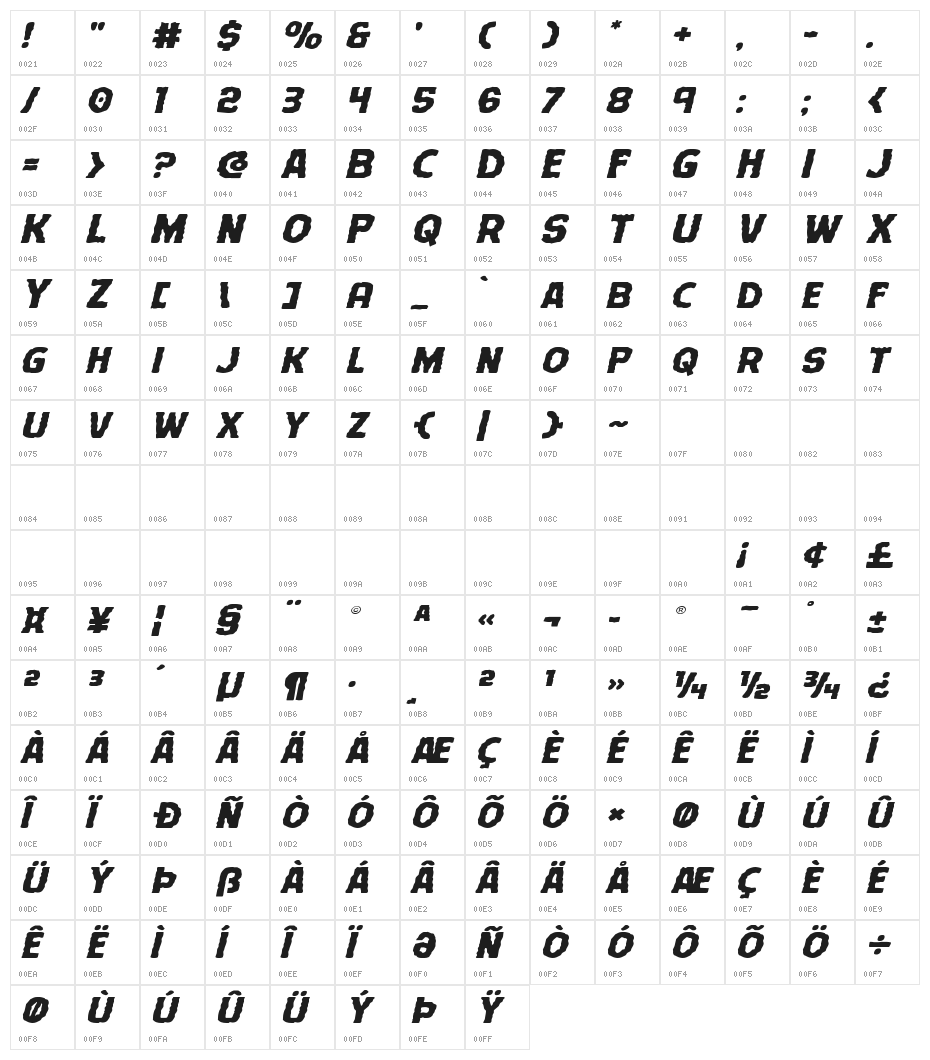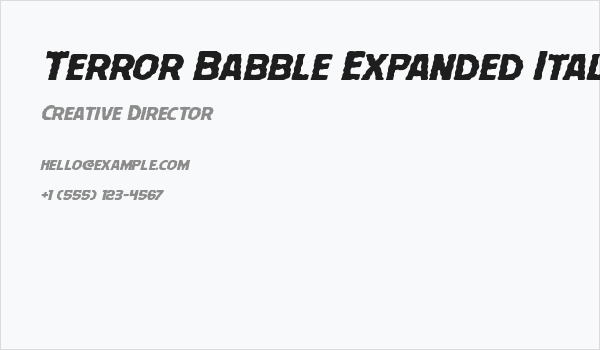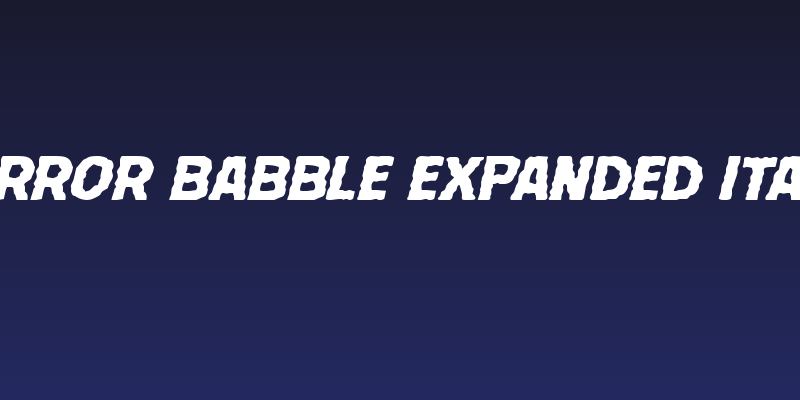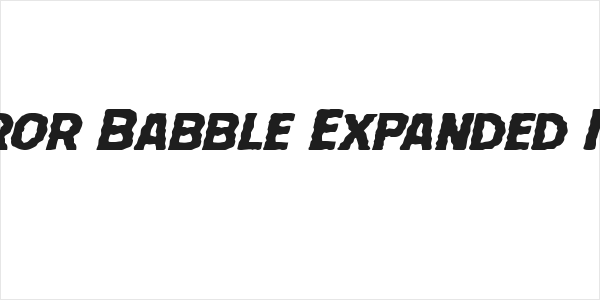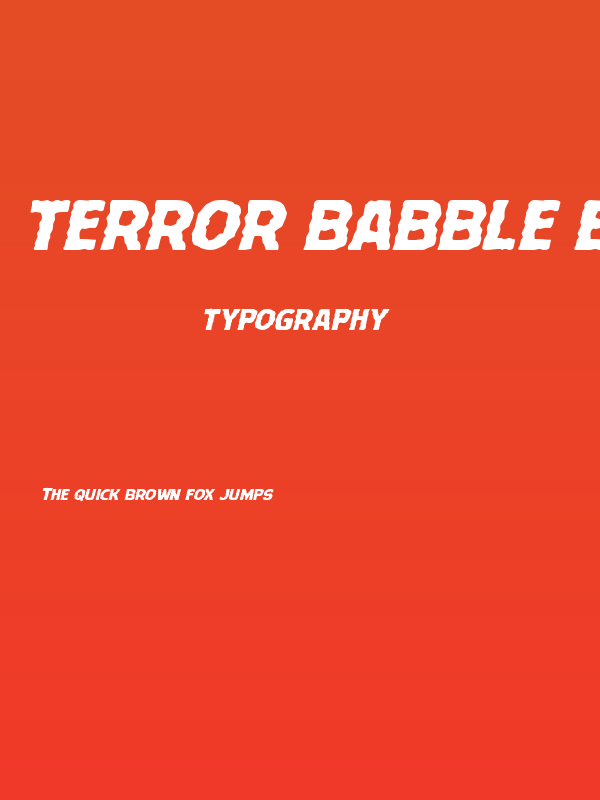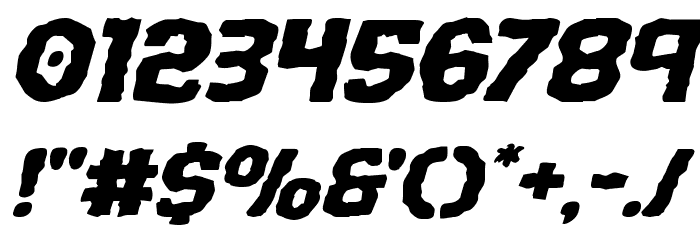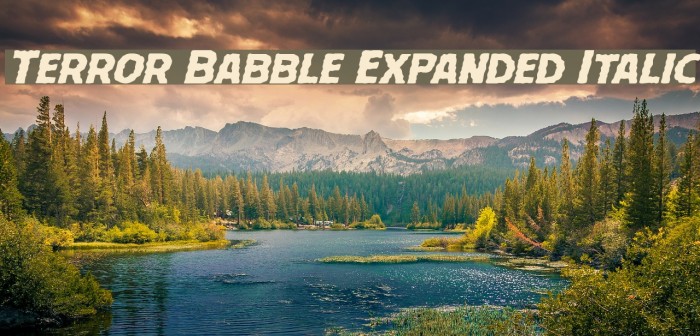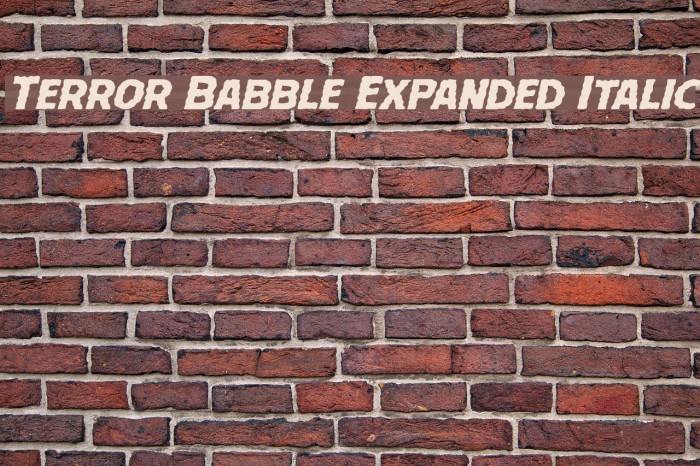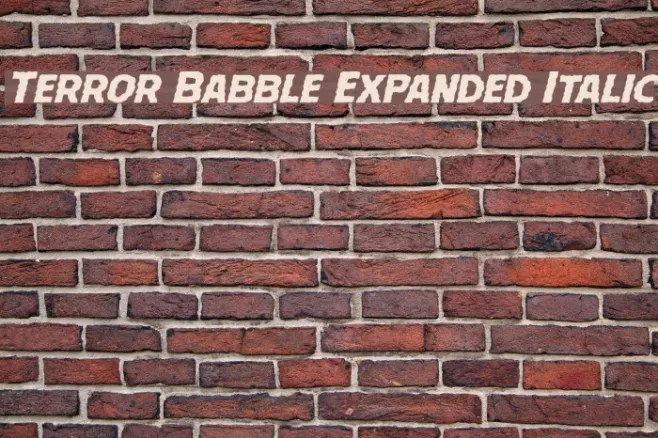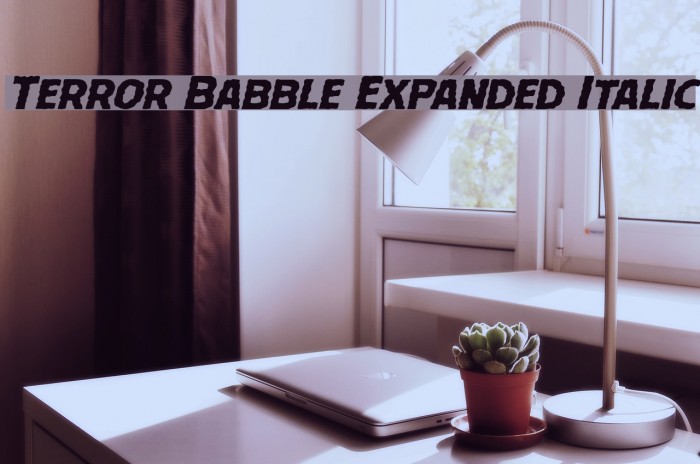
Terror Babble Expanded Italic Font
| Proyectos propuestos | Ideal for horror-themed designs, edgy posters, album covers, or any project needing a bold, rebellious look. |